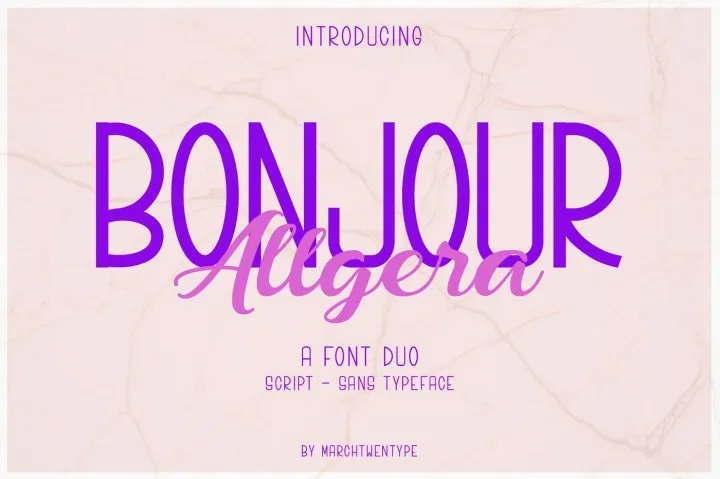
Bonjour Allgera Font Duo – Download Grátis
Olá! Presentamos uma dupla de fontes perfeitas para criar tons de design incríveis. Introduzimos a Bonjour Allgera Font. A Bonjour Allgera foi criada e compartilhada pela Marchtwentype. Esta dupla é um belo par de fontes cursiva e sans-serif. Com seu estilo calligrafiado e serif simples, dá-lhe uma elegância que pode ser usada em qualquer tipo de design que precise de um tipo forte e luxuoso. Seja para gráficos, logos ou até mesmo para textos interiores, a Bonjour Allgera será sua fonte perfeita. Descubra por si só o poder desta dupla única.